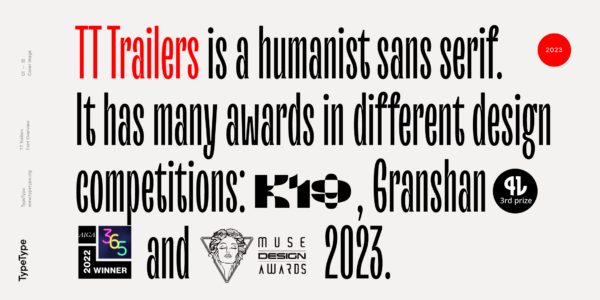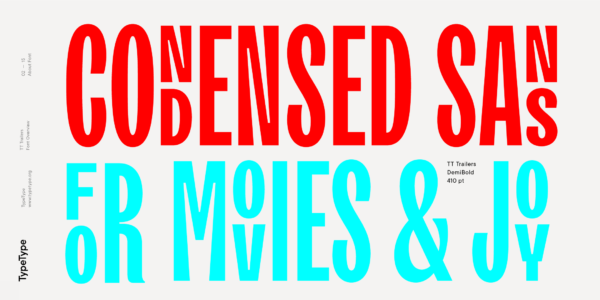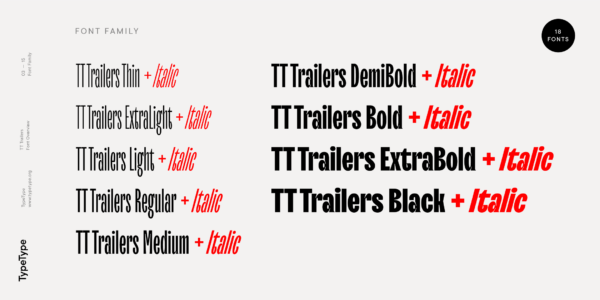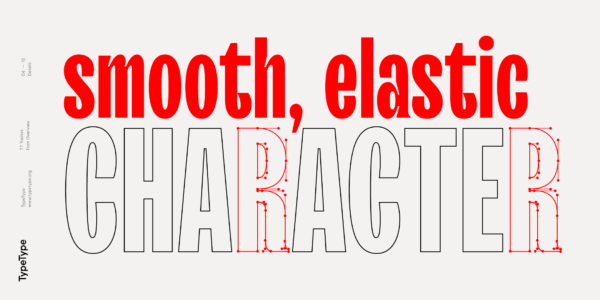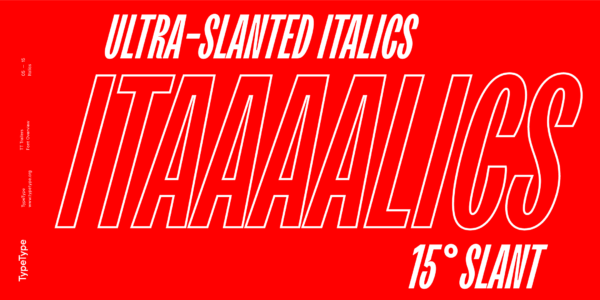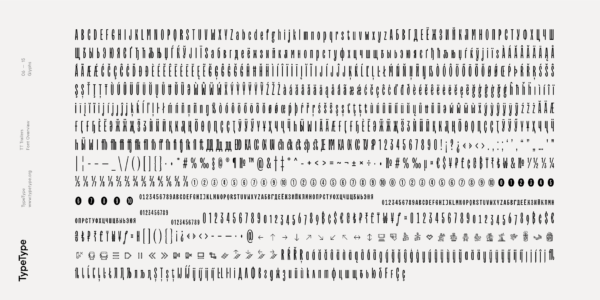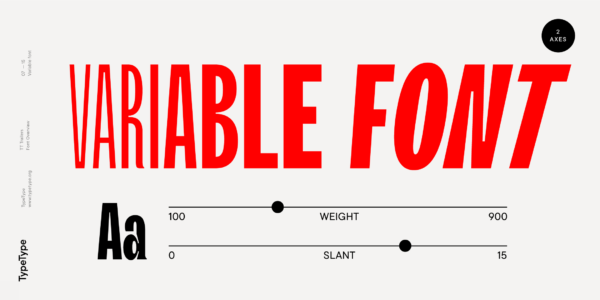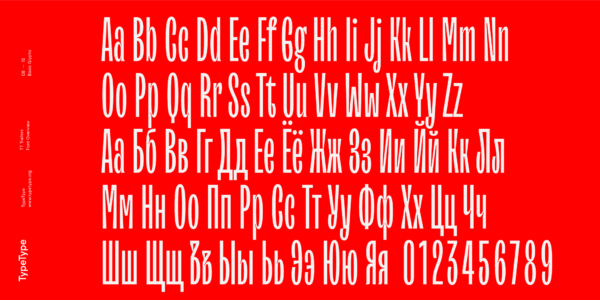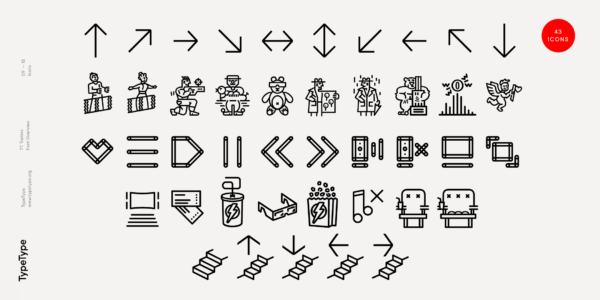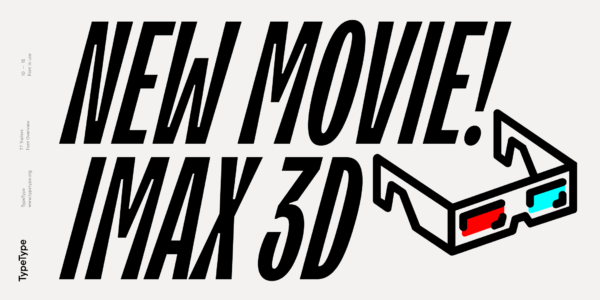
TT Trailers
TT Trailers — ТТ Трейлерс
Произносится «ТТ Трейлерс». «Trailers» — производное слово от trailer, в переводе с английского «трейлер». Буквы «TT» являются аббревиатурой названия компании.
TT Trailers — стильный и выразительный акцидентный гротеск. Его легко узнать по необычной графике: рисунок каждого знака в этом шрифте авторский, формы экспериментальные.
TT Trailers
Новый узкий гуманистический гротеск
TT Trailers
В основе TT Trailers лежит концепция сохранения количества белого: при переходе от тонкого начертания к жирному начертанию ширина знаков значительно растет, что в конечном счёте позволяет сохранить равнозначное количество белого внутри букв и между ним
TT Trailers
Новое поколение узких шрифтов для использования в титрах и киноафишах
TT Trailers
Мы сделали возможность перемещать глифы в нижний или в верхний регист
TT Trailers
О гарнитуре TT Trailers
Встречайте обновленный TT Trailers — яркий шрифт от TypeType, созданный для того, чтобы быть звездой экранов!
TT Trailers — стильный и выразительный акцидентный гротеск. Его легко узнать по необычной графике: рисунок каждого знака в этом шрифте авторский, формы экспериментальные. Среди интересных деталей — сверхузкие пропорции, необычные влития, закрытые апертуры и «подогнутые» внутрь терминалы. Италики в TT Trailers такие же эксцентричные, как и прямые шрифты. Наклон в 15 градусов выглядит абсолютно гармонично, дополняя характер гарнитуры.
Изначально TT Trailers задумывался как шрифт, идеально подходящий для киноиндустрии. Он гармонично смотрится в оформлении афиш и плакатов, идеально подходит для оформления титров. Однако на практике сфера применения этой гарнитуры гораздо шире.
Вариативный шрифт, входящий в TT Trailers, еще больше расширяет возможности его использования. Он способен меняться по оси жирности и наклону. Большое количество OpenType фич позволяет дизайнерам настраивать шрифт под разные задачи. А оригинальный набор иконок, связанный с темой кино — еще одно приятное дополнение.
В обновленной версии гарнитуры мы расширили кассовый состав, усовершенствовали техническое наполнение и доработали контуры. В частности, добавили знаки расширенной латиницы и кириллицы, новые альтернативные версии глифов и дополнительные сеты цифр.
TT Trailers отлично подойдёт для титров и афиш, для сайтов и печатной продукции. Шрифт украсит обложки журналов, вывески ресторанов и кафе, будет эстетичной составляющей постеров и плакатов.
TT Trailers — это:
• 19 начертаний: 9 прямых, 9 наклонных и 1 вариативный шрифт;
• 1242 глифа в каждом начертании;
• 42 OpenType фичи;
• Поддержка более 120 языков.
Alternative Latin a,g,y and Cyrillic a,y
Alternative l
Letters and Digits Denominators
Standard Ligatures
Discretionary Ligatures
Titling